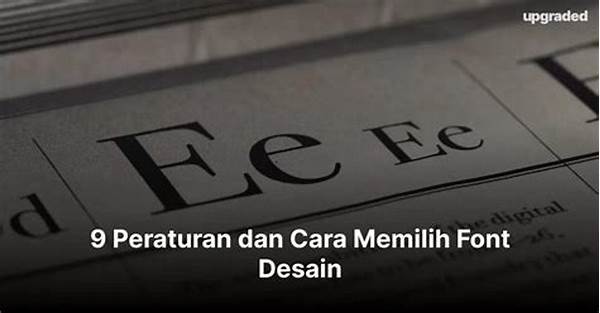
Pernah nggak sih kamu merasa nggak nyaman saat membaca suatu tulisan hanya karena font yang digunakan terlalu aneh atau sulit dibaca? Nah, itulah salah satu alasan mengapa memilih font yang tepat itu penting banget. Banyak orang yang mengabaikan pentingnya memilih font tepat, padahal hal ini bisa mempengaruhi cara orang menerima informasi dari tulisan kita. Yuk, kita bahas lebih dalam kenapa hal ini bisa jadi krusial!
Kenapa Font Itu Penting?
Kamu pernah baca buku atau artikel yang font-nya terlalu kecil atau rumit? Kadang, hanya gara-gara font yang kurang sesuai, kita jadi malas melanjutkan baca, kan? Inilah letak pentingnya memilih font tepat. Font bisa membentuk kesan pertama tentang konten yang kita sampaikan. Bayangkan saja jika kamu menulis sesuatu yang serius tapi menggunakan font Comic Sans, orang mungkin bisa salah paham dengan maksud tulisanmu. Selain itu, font juga bisa memengaruhi emosi pembaca. Font yang rapi dan mudah dibaca akan membuat orang lebih nyaman dan fokus pada isi tulisanmu. Jadi, jangan remehkan ya dan selalu coba cari font yang sesuai dengan tujuan dan audiens tulisan kita.
Font juga bisa mencerminkan identitas visual. Misalnya, saat kamu melihat sebuah brand terkenal, font yang mereka pilih pasti sudah merepresentasikan brand mereka, entah itu terlihat elegan, modern, ataupun playful. Jadi, jika kamu sedang membuat proyek atau brand sendiri, penting banget mempertimbangkan font yang bisa mewakili pesan dan image yang ingin kamu bangun. Dengan font yang tepat, kamu bisa lebih efektif dalam berkomunikasi secara visual.
Terakhir, dengan font yang sesuai, kamu juga menegaskan profesionalisme. Bayangkan saat membaca proposal bisnis dengan font yang tidak standar—rasanya sedikit meragukan, bukan? Begitulah, pentingnya memilih font tepat juga untuk memastikan audiens percaya pada apa yang sedang kita komunikasikan. Jadi, ayo lebih cermat menentukan font agar semua pesan tersampaikan dengan baik dan sesuai tujuan!
Manfaat Memilih Font Tepat
1. Meningkatkan Keterbacaan: Pilihan font yang tepat bikin teks lebih gampang dibaca. Bayangkan kalau font yang dipilih terlalu kecil atau memiliki banyak ornamen. Jadi, selalu pilih font yang nyaman di mata ya!
2. Menyampaikan Pesan Emosional: Font ternyata bisa memberi kesan atau emosi pada pembaca. Serius! Bayangkan font serif yang elegan atau sans-serif yang modern—keduanya punya feel yang berbeda.
3. Menunjukkan Profesionalisme: Memilih font tepat enggak cuma soal estetika, tapi juga bisa mengomunikasikan keseriusan dan keprofesionalan karya atau brand kita tuh.
4. Membentuk Identitas Brand: Font yang konsisten digunakan bisa membentuk dan memperkuat image brand di benak audiens. Jadikan font sebagai bagian dari identitas visual yang solid, ya!
5. Mempermudah Pemasaran: Dari kemasan hingga iklan, font yang tepat bisa meningkatkan daya tarik dan memudahkan pemasaran. Pesan yang jelas dan langsung sampai pasti lebih berkesan, bukan?
Faktor Font yang Harus Dipertimbangkan
Saat memilih font, ada beberapa faktor yang perlu diperhatikan. Pertama, pastikan font tersebut sesuai dengan tujuan dan pesan yang ingin kamu sampaikan. Bayangkan jika kita menulis undangan pernikahan dengan font gotik; rasanya aneh, bukan? Inilah pentingnya memilih font tepat untuk setiap situasi. Faktor berikutnya adalah keterbacaan. Font yang indah tapi sulit dibaca justru bisa membuat orang mengabaikan apa yang kita tulis. Selalu pilih font dengan ukuran dan spasi yang nyaman di mata.
Selanjutnya, kita harus mempertimbangkan platform yang digunakan. Font yang terlihat bagus di media cetak belum tentu tampak sama di layar digital. Dengan begitu banyaknya perangkat dan resolusi layar yang berbeda, penting untuk memastikan bahwa font yang kita pilih dapat tampil baik di segala platform. Dan jangan lupa tentang lisensi font! Beberapa font memerlukan pembelian lisensi, terutama untuk penggunaan komersial. Pastikan untuk memeriksa ini agar kita tidak melanggar aturan dan menjaga profesionalisme.
Tips Memilih Font yang Tepat
1. Kenali audiensmu. Mengetahui siapa yang akan membaca atau melihat karya kita bisa membantu dalam memilih font yang sesuai.
2. Uji coba berbagai kombinasi font sebelum memutuskan yang terbaik. Gabungkan serif dengan sans-serif untuk menemukan gaya yang pas.
3. Gunakan software atau tools desain untuk melihat tampilan font secara menyeluruh. Ini bisa membantu memberikan gambaran lebih jelas.
4. Tetap konsisten, terutama bila ini untuk brand atau proyek jangka panjang. Konsistensi membuat identitas lebih mudah dikenali.
5. Jangan lupakan ukuran dan spasi antar huruf. Kedua elemen ini sama pentingnya dengan memilih jenis font.
6. Pertimbangkan emosi yang ingin disampaikan. Font yang tepat bisa mempengaruhi bagaimana pesan diterima audiens.
7. Cek keterbacaan di berbagai ukuran. Pastikan teks tetap bisa dibaca dengan jelas di ukuran kecil maupun besar.
8. Pilih font yang berbeda untuk judul dan isi agar lebih dinamis, tetapi tetap harmonis.
9. Hindari penggunaan terlalu banyak jenis font dalam satu karya agar tidak membingungkan.
Kesimpulannya, jangan pernah meremehkan kekuatan dari sebuah font. Setiap huruf yang kita pilih, bahkan bentuk dan ukurannya, memiliki peran besar dalam proses komunikasi tulisan. Di dunia yang serba visual ini, memiliki pemahaman yang baik tentang pentingnya memilih font tepat adalah investasi jangka panjang untuk setiap karya yang kita hasilkan. Semoga setelah membaca artikel ini, kita jadi lebih bijak dalam memutuskan font untuk setiap proyek kita, ya!